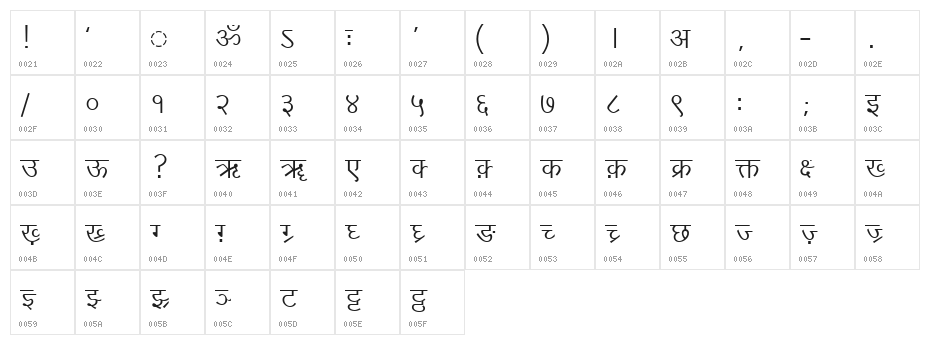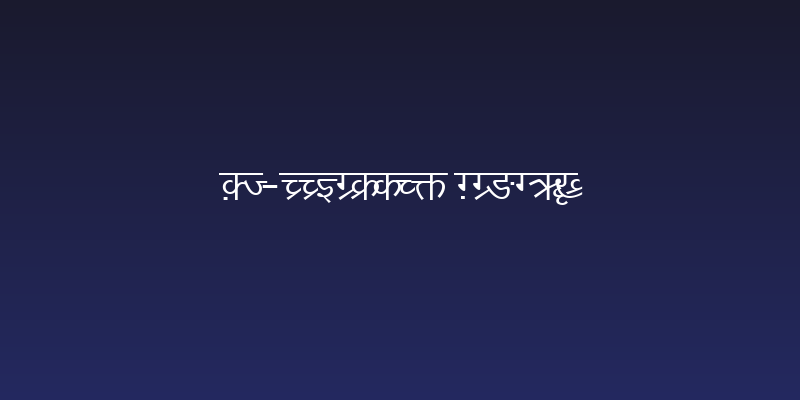
DV-TTYogesh Normal Font
| 整体风格 | Traditional |
| 使用场景 | Headlines, Body text, Cultural publications |
| 推荐项目 | Ideal for cultural publications, educational materials, and digital content that require a traditional yet readable Devanagari script. |